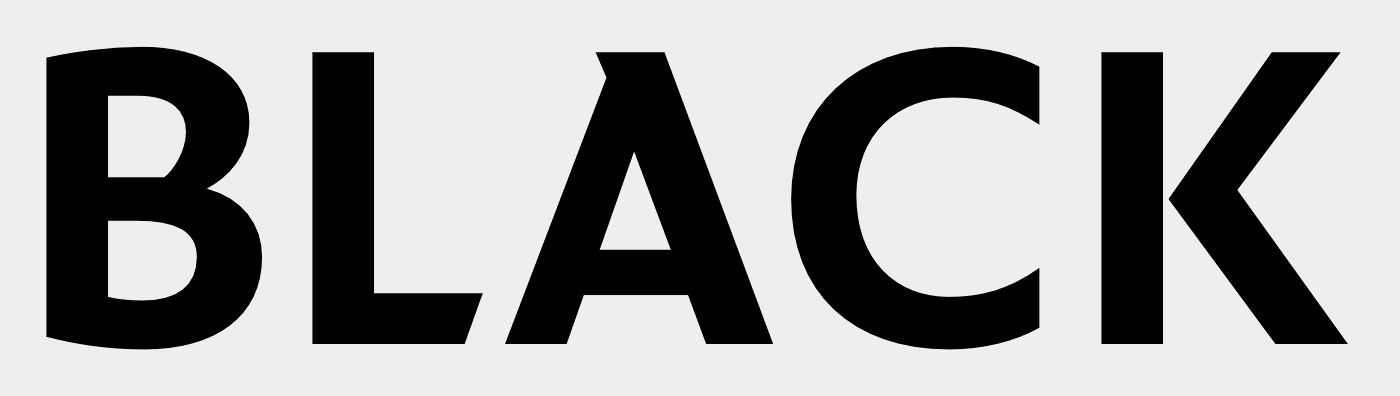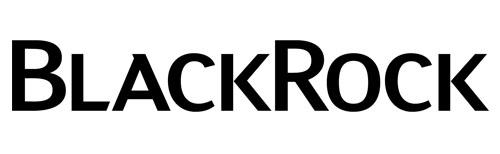
Logo-Schrift „Blackrock“ gesucht
Suche Logo-Schrift von „BlackRock“ oder eine ähnliche Schrift. Beachte: charakteristischer Anstrich beim „A“.
Quelle: www.blackrock.com, abgerufen am 06.09.2017
Um das Rätsel weiterzubringen: Das Logo ist von der Investment Company "BlackRock", www.blackrock.com
In pdfs findet sich nur ein vektorisiertes Logo und keine passende Schrift, das hab ich schon nachgeschaut.